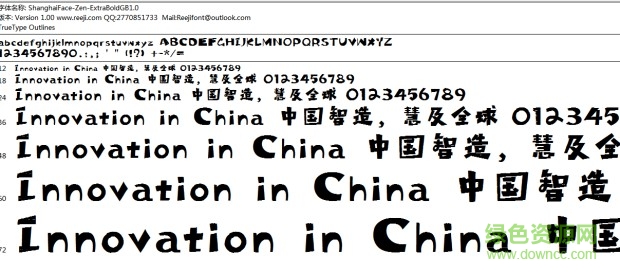
shanghaiface zen extraboldgb1.0和2.0两款字体是绿色资源网为大家搜集的海派腔调禅大黑简合集下载包,结构紧凑,疏密设计精巧,粗细对比强烈,非常有韵味,欢迎下载!
字体粗细度采用了粗的Bold的设计,字形风趣幽默,可以带来全新的视觉体验,夸张的笔画设计,笔画对比强烈字与字大小差距较大,字体重心做了基本规范,部分字如海字采用凹凸不齐的边缘来表达上海的海纳百川的精神,全部字采用标准汉字的笔画识别方法。